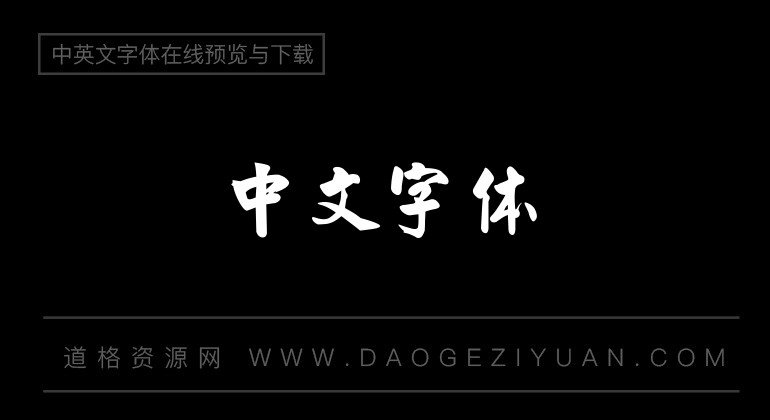
中国龙豪行书
中国龙豪行书是一款具有中国传统文化特色的汉字字体,由中国知名字体设计师王晓涛设计。它以中国龙的形象为灵感,结合了古典书法的精髓,融入了现代设计元素,营造出一种传统与现代并存的经典字体。中国龙豪行书具有良好的识别度和可读性,适用于各种类型的文字,可以用于商业、广告、网页设计等领域。
中国龙豪行书是一款非常不错的手写艺术字体,具有很好的视觉感,适合于文化类的宣传设计、商业类品牌的广告和产品包装设计以及个性化文字排版等较多场景。